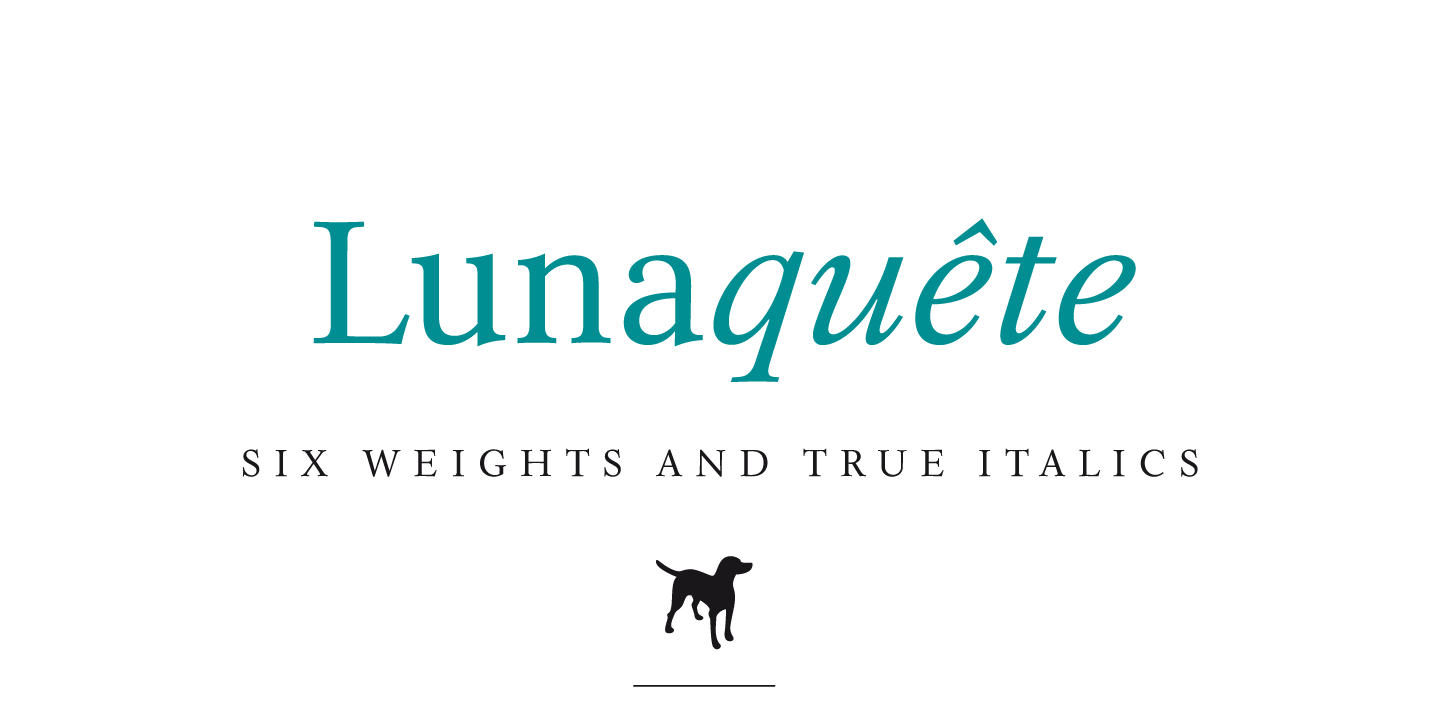
Liebe Kollegen,
vor einigen Tagen veröffentlichte ich eine meiner Schriften. Ich möchte sie euch nun hier im Forum vorstellen. Es ist einer von mehreren Schriftentwürfen, die ich z. T. vor längerer Zeit gezeichnet und nun als Font realisiert habe. Ursprünglich konzipiert für ein konkretes Buchprojekt, schaffte ich aber die Fertigstellung aus Zeitgründen nicht.
Lunaquête
Die „Lunaquête“ wurde in erster Linie für den Buchsatz und als Druckschrift entworfen. Sie sollte relativ neutral, gut lesbar und zeitlos sein. Das war zumindest meine Intention. Sie hat 12 Schnitte – 6 Stärken mit Kursiver.
Zur Schrift selbst will ich mich nicht äußern, weil das keinen Sinn macht, ohne sie im Druck gesehen zu haben. Und ausgedruckt habe ich das PDF noch nicht.
Die Schrift kann im Grunde genommen nur nach einem Maschinendruck beurteilt werden. Zur Beurteilung habe ich Andrucke im Offset- und Digitaldruck erstellen lassen. Obwohl es sich um Qualitätsdrucke handelt, sind Unterschiede zwischen den beiden Druckverfahren erkennbar. Ein Bürodrucker sagt nicht viel aus.
Ein Bürodrucker sagt nicht viel aus.
Meiner druckt ziemlich eng an den original Formen. Aber das wollte mir schon beim letzten Mal niemand glauben. Nicht, dass ich glauben würde, der Druck sei optimal. Aber er ist schon ziemlich gut. Zumindest war er das, bevor er angefangen hat Streifen zu drucken. (Konstruktionsfehler der Tonerkartusche.) Ich hatte mir vor dem Kauf mit Hilfe eines Mikroskops aufgenommen Fotos von der in Lesegraden gedruckten Schrift (das kleine a der Palatino) bei Druckerchannel besorgt und in Photoshop die Outline des Fonts darüber gelegt.
Edit: Soll heißen, dass ich einfach keine Schriften mehr am Bildschirm beurteile. Ich bin der Ansicht, dass sich die Qualität einer Brotschrift kaum in Schaugrößen beurteilen lässt. Und in Lesegraden macht es am Bildschirm keinen Sinn. Ich mach das zumindest nicht mehr.
Sehr schön! Ein kleiner Schönheitsfehler, den leider viele Schriften haben, ist die Implementierung der ungarischen Diakritika.
Alle akutartigen Diakritika sollten dieselbe Neigung haben und am besten auch dieselbe Größe und beim Doppelakut eine gleich große Lücke. http://ű.net/samples/
Ein kleiner Schönheitsfehler, den leider viele Schriften haben, ist die Implementierung der ungarischen Diakritika.
Den Schönheitsfehler habe ich bewusst eingebaut. Die Versal-Akzente könnten sonst mit einer darüberstehenden Unterlänge kollidieren. Kommt natürlich auf den Zeilenabstand an. Ich habe das abgewogen und mir  überlegt und bin dann zum Entschluss gekommen, diese so flach anzusetzen. Fällt im Mengensatz nicht unbedingt auf. Ein zu enger Zwischenraum zur Unterlänge wäre dann störend.
Die Druckqualität meines Druckers hat leider wegen des Konstruktionsfehlers der Kartusche stark abgenommen. Soweit ich das noch über einen Ausdruck mit meinem Drucker beurteilen kann, ist die Schrift recht gut lesbar. Und sie gefällt mir. Ich habe nur Seite 18 ausgedruckt.
Eine Sache ist mir aber negativ aufgefallen: Die Zeichenfolge ch, z. B. in dem Wort ich. Das h wirkt vergleichsweise zu schmal bzw. das c zu breit.
Danke. Muss mir zuerst aber alles ein wenig vorbereiten.
Eine Sache ist mir aber negativ aufgefallen: Die Zeichenfolge ch, z. B. in dem Wort ich. Das h wirkt vergleichsweise zu schmal bzw. das c zu breit.
Gut beobachtet.
Es ist jedoch aus meiner persönlichen Sichtweise heraus so entstanden. Ich wollte generell die „runden“ Buchstaben etwas breiter gestalten als in den meisten Antiquaschriften. Das sind dann „c“ „e“ „o“.
Aber trotzdem nicht ganz unüblich. Mir fällt dazu als Vergleich die „Perpetua“ ein, die ein ähnlich proportionales Verhältnis vom „c“ zum „h“ aufweist.
Das sind dann „c“ „e“ „o“.
Zwischen o und h ist der Abstand größer. Ich würde gerne mal ch mit etwas größerem Abstand sehen. Im Moment stolpere ich über ch. Und zu stolpern heißt, dass die Lesbarkeit nicht optimal ist. Der Text ist aber auch im Vergleich zu den Textproben anderer Typedesigner/Foundries recht sperrig. Rein werbetechnisch tust dir meiner Meinung nach damit keinen Gefallen. (Blindtext halte ich übrigens auch nicht für geeignet.) Über das Wort »Gleichwohl« bin ich z. B. nicht gestolpert.
Edit: Was sich bei Specimen immer anbietet, ist, etwas über die Entwicklung der Schrift zu schreiben. Warum hast du Bedarf für eine weitere Brotschrift gesehen? Welche Lücke soll die Schrift füllen? Was hat dich motiviert? Wie hat sich die Schrift über die Zeit entwickelt? Ein paar technische Aspekte. Und so weiter. Ich mag z. B. die Präsentation der DTL Fleischmann.
Sollten wir daraus nicht vielleicht mal einen Artikel für Typedesigner machen, statt jeweils nach der Veröffentlichung jeder neuen Schrift den Fehler wieder und wieder anzukreiden?
Aber klar, ich wollte das schon lange mal allgemeingültig aufschreiben. Ich nehme an, du hättest es gern auf Englisch (für den Guru) und auf Deutsch?